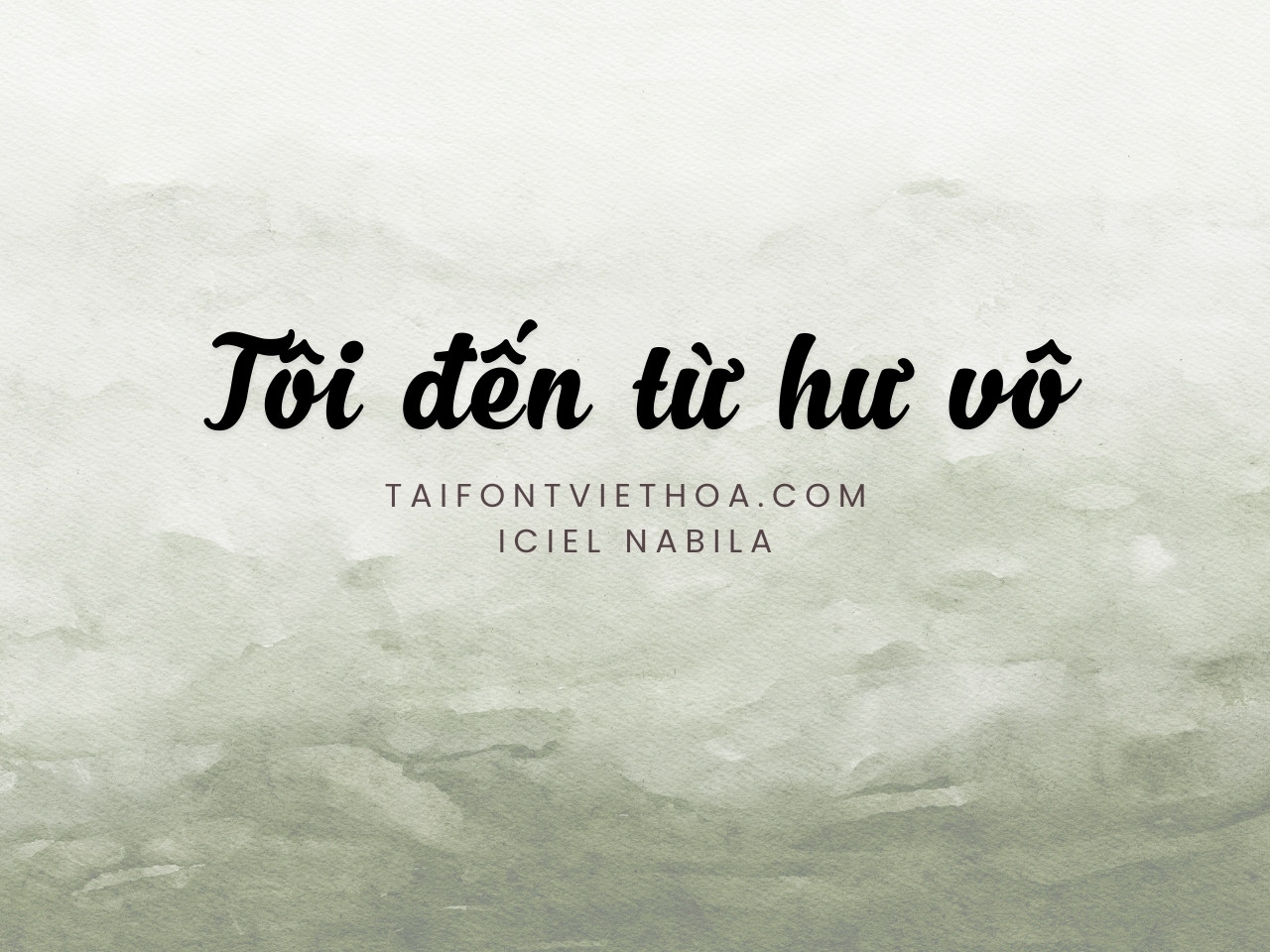
Giới thiệu về font iCiel Nabila – Bay bổng, hiện đại và nổi bật
iCiel Nabila là một kiểu chữ trưng bày (display) hiện đại mang phong cách viết tay nghệ thuật, kết hợp giữa sự mềm mại và cấu trúc hình học phá cách. Font được Việt hóa bởi iCiel, hỗ trợ đầy đủ tiếng Việt cùng hơn 60 ngôn ngữ khác. Với các đường cong uốn lượn, kết cấu mượt mà và độ dày đồng đều, Nabila tạo nên sự nổi bật và thu hút ngay từ ánh nhìn đầu tiên – đặc biệt phù hợp cho các thiết kế mang tính biểu cảm cao.
Font này được taifontviethoa.com chọn lọc và ứng dụng thử nghiệm trong nhiều thiết kế thực tế như tiêu đề poster, logo thương hiệu, bao bì sản phẩm thủ công, hoặc các ấn phẩm sáng tạo dành cho ngành thời trang, mỹ phẩm hoặc lifestyle. Sự mềm mại kết hợp với hình dáng chữ hiện đại khiến Nabila trở thành một lựa chọn lý tưởng để truyền tải thông điệp đầy cá tính.
Đặc điểm thiết kế và ứng dụng nổi bật của font iCiel Nabila
Font Nabila có cấu trúc viết tay giả calligraphy, với các nét chữ nối liền, đường cong nhịp nhàng và độ nghiêng nhẹ tạo cảm giác chuyển động liên tục. Kiểu chữ mang đậm tính nữ tính, thanh lịch nhưng không quá cầu kỳ, dễ kết hợp trong cả các thiết kế cổ điển và hiện đại.
iCiel Nabila rất phù hợp với các ngành nghề như thời trang, thiệp cưới, mỹ phẩm, ẩm thực thủ công, sản phẩm handmade hoặc các thương hiệu cần thể hiện sự nhẹ nhàng và uyển chuyển. Ứng dụng tiêu biểu gồm: thiết kế logo cá nhân, typography mạng xã hội, bao bì sản phẩm cao cấp, tiêu đề blog thời trang, hoặc các chiến dịch quảng cáo mang đậm tính thẩm mỹ.